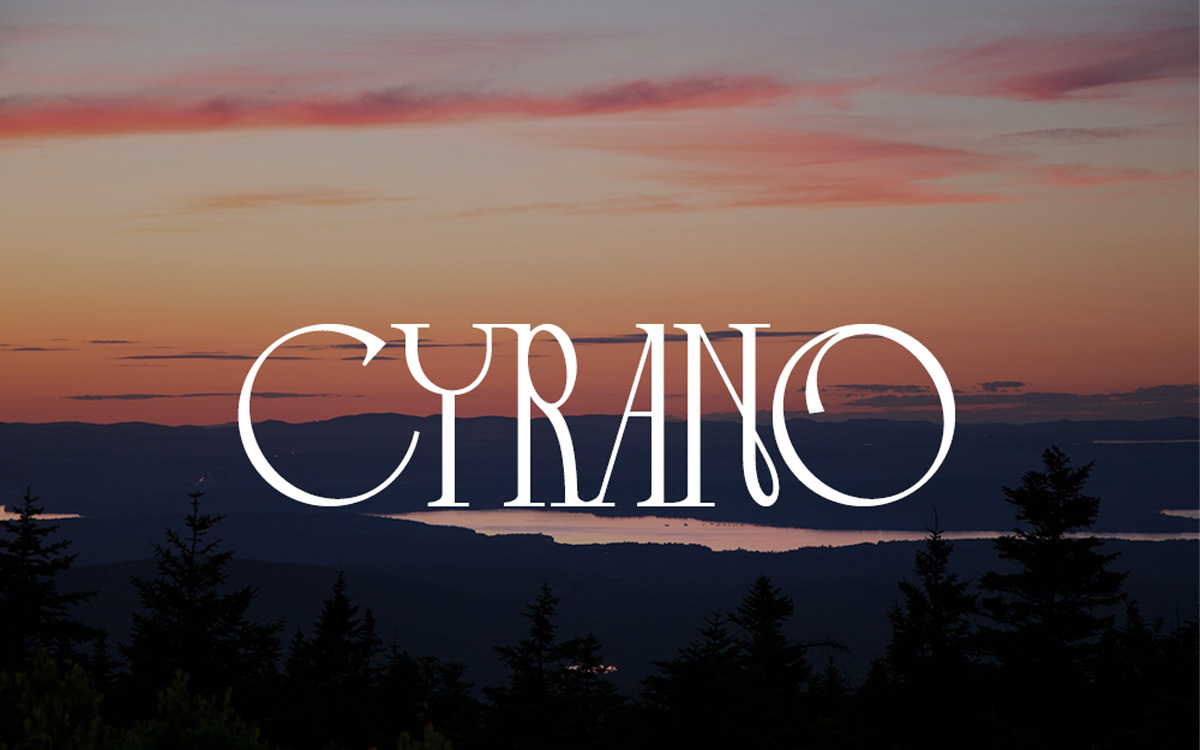
Font Chữ Sang Trọng SVN-Cyrano Việt Hoá
Trong thế giới thiết kế đồ họa chuyên nghiệp, nghệ thuật chữ (Typography) không chỉ đóng vai trò truyền tải thông điệp văn bản mà còn là yếu tố định hình phong cách và giá trị của toàn bộ thương hiệu. Font chữ sang trọng SVN-Cyrano Việt hoá chính là một kiệt tác nghệ thuật đáp ứng hoàn hảo các tiêu chuẩn khắt khe nhất về tính thẩm mỹ quý phái, thanh lịch. Với bộ ký tự được Việt hóa tỉ mỉ, phông chữ này hứa hẹn sẽ nâng tầm mọi sản phẩm thiết kế, từ bộ nhận diện thương hiệu cao cấp đến các ấn phẩm truyền thông thời thượng.
Font Chữ Sang Trọng SVN-Cyrano Việt Hoá – Giải Pháp Thiết Kế Đẳng Cấp Và Tinh Tế
Sự kết hợp giữa nghệ thuật tạo hình chữ cổ điển và tư duy thiết kế hiện đại đã tạo nên font chữ sang trọng SVN-Cyrano Việt hóa. Được truyền cảm hứng từ những kiểu chữ Serif mang tính biểu tượng của Châu Âu, SVN-Cyrano sở hữu các đường nét uyển chuyển, tỷ lệ hình học chuẩn mực cùng thần thái kiêu sa khó cưỡng. Đối với các nhà thiết kế đồ họa, chuyên viên sáng tạo nội dung hay nhà làm bản tin thời trang, việc sở hữu bộ phông chữ này trong thư viện cá nhân là một lợi thế lớn để kiến tạo nên những tác phẩm đồ họa mang đậm dấu ấn thượng lưu.
SVN-Cyrano không đơn thuần là một kiểu chữ thông thường mà là một công cụ truyền tải cảm xúc mạnh mẽ. Khi áp dụng vào các tiêu đề tạp chí, bìa sách, bao bì sản phẩm hay biểu trưng thương hiệu, font chữ này lập tức thu hút thị giác của người xem nhờ vẻ đẹp kiêu hãnh và tính đăng đối hài hòa. Hơn thế nữa, quá trình Việt hóa chuyên nghiệp đảm bảo từng dấu thanh, dấu mũ trong tiếng Việt đều được xử lý tinh xảo, giữ nguyên tinh thần thiết kế nguyên bản của tác giả gốc.
1. Đường nét nét thanh nét đậm tương phản đỉnh cao và phong cách tân cổ điển
Điểm đặc trưng nổi bật nhất của font chữ sang trọng SVN-Cyrano Việt hóa chính là sự chênh lệch độ dày – mỏng được tính toán một cách hoàn hảo giữa các nét chữ. Sự tương phản rõ rệt này mang lại nhịp điệu thị giác sống động, tạo nên cảm giác quý phái, lộng lẫy và vô cùng chuyên nghiệp. Các chân chữ (serif) được gọt giũa sắc nét, tinh xảo nhưng vẫn giữ được độ mềm mại nhất định, giúp tổng thể văn bản vừa vững chãi vừa thanh thoát.
Phong cách tân cổ điển (Neoclassical) ẩn chứa trong từng chữ cái giúp SVN-Cyrano dễ dàng hòa quyện vào các không gian thiết kế mang hơi hướng xa xỉ. Dù bạn sử dụng font chữ này ở kích thước tiêu đề lớn (Display) hay các dòng phụ đề nổi bật, bộ kỹ thuật tạo hình chân chữ độc đáo vẫn duy trì sự sắc nét tuyệt đối, không gây rối mắt cho người thưởng lãm.
• Tỷ lệ nét chữ tương phản cao giúp thu hút sự chú ý tức thì vào các nội dung trọng tâm.
• Chân chữ Serif tinh tế tạo cảm giác tin cậy, lâu đời và có bề dày lịch sử.
• Kiến trúc chữ mở rộng giúp các không gian âm (negative space) thở tốt hơn, tạo độ thoáng cho bố cục.
2. Bộ ký tự Việt hóa hoàn chỉnh, tối ưu hóa chuẩn Unicode và Kerning chuyên nghiệp
Một trong những nỗi lo lớn nhất của các nhà thiết kế tại Việt Nam khi sử dụng các font chữ nước ngoài là lỗi font, dính chữ hoặc các dấu thanh (sắc, huyền, hỏi, ngã, nặng, mũ) bị đặt sai vị trí làm mất đi thẩm mỹ của tổng thể. Với phiên bản SVN-Cyrano Việt hóa, toàn bộ bộ ký tự tiếng Việt đã được tinh chỉnh tỉ mỉ theo đúng quy chuẩn Typography quốc tế.
Hệ thống dấu câu được vẽ tay chuẩn xác, đảm bảo độ hài hòa về khoảng cách và kích thước so với ký tự gốc. Các chỉ số Kerning (khoảng cách giữa các chữ cái) và Tracking đã được lập trình sẵn tối ưu, giúp câu từ hiển thị trôi chảy mà người thiết kế không cần mất quá nhiều thời gian để canh chỉnh thủ công. Điều này giúp tăng tốc độ làm việc cũng như đảm bảo tính nhất quán cho các dự án thiết kế quy mô lớn.
1. Hỗ trợ đầy đủ các bản mã tiếng Việt phổ biến nhất hiện nay như Unicode, UTF-8.
2. Tương thích tuyệt đối trên cả hệ điều hành Windows và macOS mà không phát sinh lỗi hiển thị.
3. Các dấu tiếng Việt được tích hợp khéo léo, không làm đứt gãy nét chữ nguyên bản.
3. Tích hợp các tính năng OpenType phong phú với Ligatures và Alternates độc đáo
Một điểm cộng rất lớn dành cho font chữ sang trọng SVN-Cyrano Việt hóa là sự hỗ trợ vượt trội các tính năng OpenType cao cấp. Nhà thiết kế có thể dễ dàng biến hóa biến thể của các ký tự nhờ vào hệ thống chữ nối (Ligatures) và các chữ cái thay thế (Stylistic Alternates) vô cùng phong phú. Việc bổ sung các nét uốn lượn nghệ thuật ở đầu hoặc cuối từ giúp tạo ra những dòng chữ ấn tượng, mang tính cá nhân hóa cao.
Tính năng này cực kỳ hữu ích khi bạn thiết kế Logo, Monogram hay tiêu đề cho các sự kiện đặc biệt như tiệc cưới, lễ trao giải, triển lãm nghệ thuật. Chỉ với vài cú nhấp chuột trong các phần mềm thiết kế chuyên nghiệp như Adobe Photoshop, Illustrator hay InDesign, bạn có thể biến một dòng chữ bình thường thành một tác phẩm thư pháp hiện đại cuốn hút.
• Ligatures (Chữ nối): Kết hợp tự nhiên giữa các cặp chữ cái như fi, fl, st, ct giúp tổng thể liền mạch.
• Alternate Characters: Cung cấp nhiều lựa chọn hình dáng chữ khác nhau cho các chữ cái A, R, K, Q, Swash…